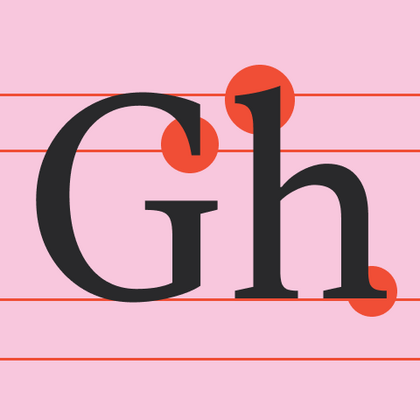
Шрифты с засечками (Антиквы)
Антиквы — это общее название для разных групп шрифтов с засечками. Первые антиквы появились очень давно, в эпоху Возрождения, что отражено в названии: в переводе с латинского языка anticuus обозначает «древний».
Благодаря засечкам типографы прошлого получали более качественный оттиск, минимизируя изнашиваемость самих букв. Сегодня антиквы активно используются в печати, особенно популярны в качестве книжных или журнальных шрифтов.
Помимо засечек, для антикв характерен высокий контраст. Антиквы — широкая группа шрифтов, которая делится на разные категории. По сфере применения выделяют текстовые и заголовочные антиквы.
Чаще всего встречается деление антикв по историческому периоду. Выделяют антикву старого стиля, переходную антикву, антикву нового стиля и брусковую антикву.
Антиквой старого стиля называют первые шрифты, получившие распространение в XV–XVII веках и обладающие чертами рукописных букв. Главными особенностями антиквы старого стиля являются такие элементы, как наклонные овалы у букв и несимметричные засечки.
Интересным примером шрифта из коллекции TypeType станет ТТ Белс (TT Bells), обладающий чертами старостильных шрифтов, но разработанный с использованием современных геометрических приёмов.
Переходная антиква отличается от предыдущей высоким контрастом букв и симметричными засечками. Такой тип шрифтов выглядит строго и аккуратно, поэтому часто используется для официальной документации и книг.
В нашей коллекции вы найдёте уникальный шрифт ТТ Марксиана (TT Marxiana), вдохновлённый дореволюционными шрифтами Санкт-Петербургского журнала «Нива». Семейство ТТ Марксиана содержит 3 шрифта, один из которых, ТТ Марксиана Антиква (TT Marxiana Antiqua), является примером шотландской антиквы, промежуточной между переходной и новостильной.
Антиква нового стиля появилась в конце XVIII века. К этой категории относят шрифты, у которых моноширинные пропорции и сильный контраст. Среди основных сфер использования печать книг, брошюр и журналов.
Яркими примерами новостильных антикв являются ТТ Женеверс (TT Jenevers) и ТТ Барэлс (TT Barrels).
Последний подвид антикв — брусковая. Период их распространения в типографике приходится на начало XIX века. Для таких шрифтов характерны мощные засечки прямоугольной формы и малый контраст. Брусковые шрифты идеальны в качестве заголовочных шрифтов для рекламных постеров и афиш.
Среди работ TypeType отличным примером брускового шрифта выступает гарнитура ТТ Рационалист (TT Rationalist), идеально подходящая для заголовков книг, журналов и другой печатной продукции.
На сегодняшний день антиквы обладают широкой сферой применения, но чаще всего используются в качестве заголовочных или текстовых книжных шрифтов. Такие шрифтовые гарнитуры привлекают внимание и обладают хорошей читаемостью. В коллекции TypeType вы найдёте антиквы самых разных характеристик: от выдержанных до выразительных.
Среди антикв с характером особой популярностью пользуется коллекция из шести дисплейных заголовочных антикв ТТ Рикорди (TT Ricordi): ТТ Рикорди Нобили (TT Ricordi Nobili), ТТ Рикорди Аллегрия (TT Ricordi Allegria), ТТ Рикорди Грето TT Ricordi Greto, ТТ Рикорди Мармо (TT Ricordi Marmo), ТТ Рикорди Фульмини (TT Ricordi Fulmini), ТТ Рикорди Тоди (TT Ricordi Todi), а также ТТ Ливрет Дисплей (TT Livret Display).
Бестселлеры среди текстовых антикв студии TypeType — ТТ Нормс Про Сериф (TT Norms® Pro Serif) и ТТ Ливрет Текст (TT Livret Text).
TT Odellia — старостильная антиква с современным рисунком, вдохновлённая венецианскими шрифтами и классической музыкой.
TT Nooks Serif — акцидентная новостильная антиква с лёгким налётом эгоцентричности. У неё острый и твёрдый, при этом элегантный и статный характер.
TT Bells сочетает в себе элегантную мягкость антиквы с непростым и дерзким характером, который выражается в прямых срезах и клинообразных засечках. В основе шрифта лежит ширококонечное перо, характерное для старостильных шрифтов, создающее эти атмосферные срезы и засечки.
TT Jenevers стилистически относится к голландским антиквам нового стиля. В гарнитуре присутствуют характерные детали, свойственные голландским антиквам — это ассиметричная форма засечек или нерегулярный наклон овалов.
TT Regins — шотландская новостильная антиква с королевским характером. Яркий контраст и острые треугольные засечки придают этому шрифту строгий и властный нрав.
TT Ricordi Allegria — современная ленточная антиква, отличительные особенности которой, гиперболизированная разноширинность в пропорциях, контраст между штрихами, клиновидные окончания штрихов и отсутствие традиционных засечек.
TT Bakers — пластичная антиква с нежным и живым характером. Этот шрифт похож на свежую выпечку: он тёплый и мягкий, особенно в жирных начертаниях.
TT Tsars является коллекцией акцидентных титульных антиквенных шрифтов, стилизованных под начало, середину и конец XVIII века. В основу проекта легли титульные шрифты, то есть те шрифты, которыми оформлялись, в частности, книжные титулы.
TT Polls берет свое начало как современный модульный брусковый шрифт. При создании шрифтового семейства TT Polls мы держали в голове его использование в дизайне на спортивную тематику, но финальная версия TT Polls отлично подходит и для более казуального дизайна и сфер применения.